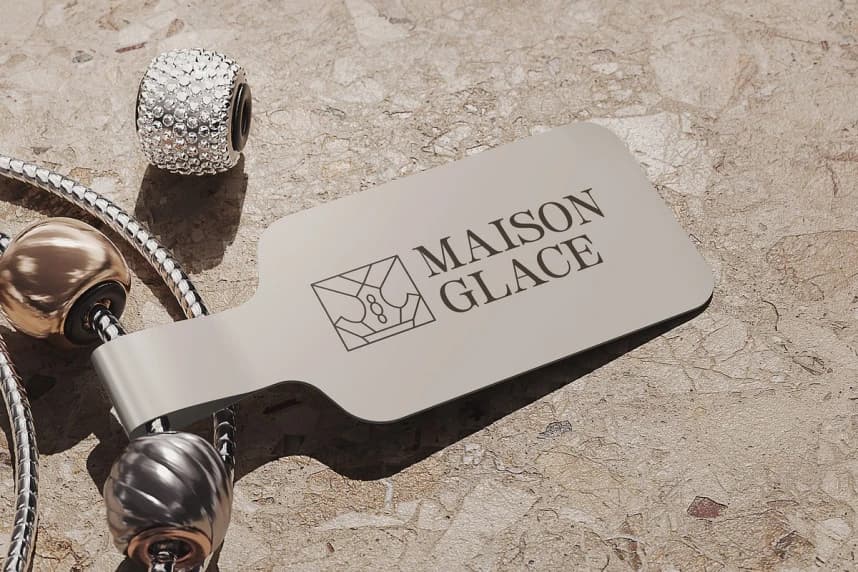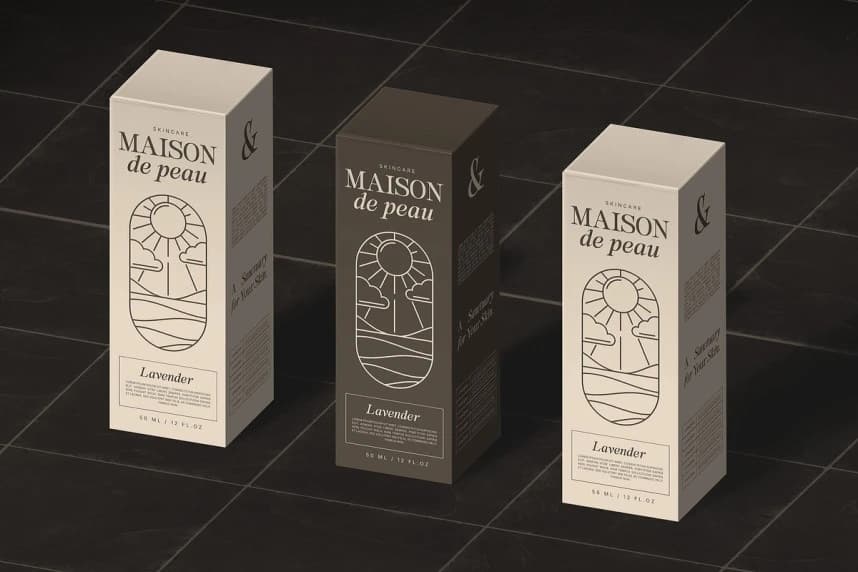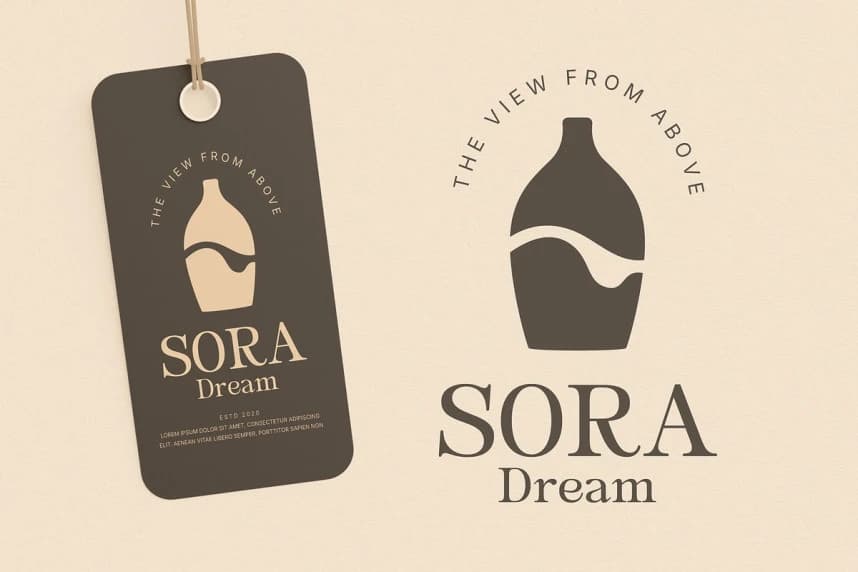
Parnelle Font, modern zarafetin ustalık dersidir. Bu display serif, Youthlabs Studio tarafından titizlikle tasarlanmış olup klasik harf biçimlerini çağdaş bir zarafetle kusursuzca harmanlar ve hem köklü hem de taze bir his veren bir yazı tipi yaratır.
Parnelle Font, modern zarafetin bir ustalık dersi. Bu gösterişli serif, Youthlabs Studio tarafından özenle tasarlanmış olup, klasik harf biçimlerini çağdaş bir zarafetle kusursuz bir şekilde harmanlayarak hem geçmişe ait hissi veren hem de taze bir yazı tipi yaratır.